作为设计师,时常需要在网络上关注各类字体资讯、搜字体去了解各种字体,电脑里也是有一个丰富的小字体库的存在。虽然字体下载了许多可是常用的字体还是固定的几款,甚至还会影响加载,这次小编要分享几款设计大神们悄悄再用的超高实用性字体给大家。
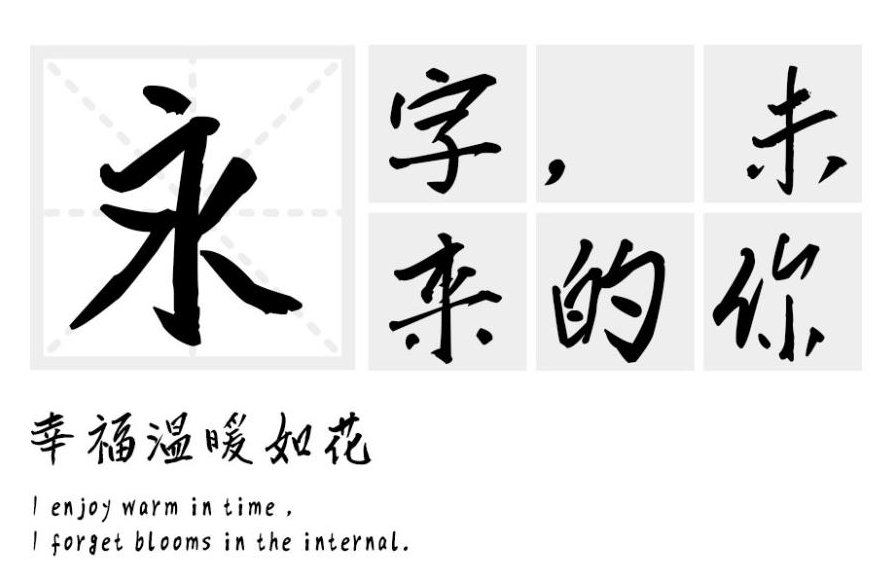
汉标儒雅楷书:这款字体设计遵循着中国传统技法,融合百家之长。浑然天成的字体风格,视觉效果典雅大方。字体结构严谨、比例合理,整体上给人一种舒展自如、赏心悦目的感受。适用于广告、屏幕显示、正文等方面。
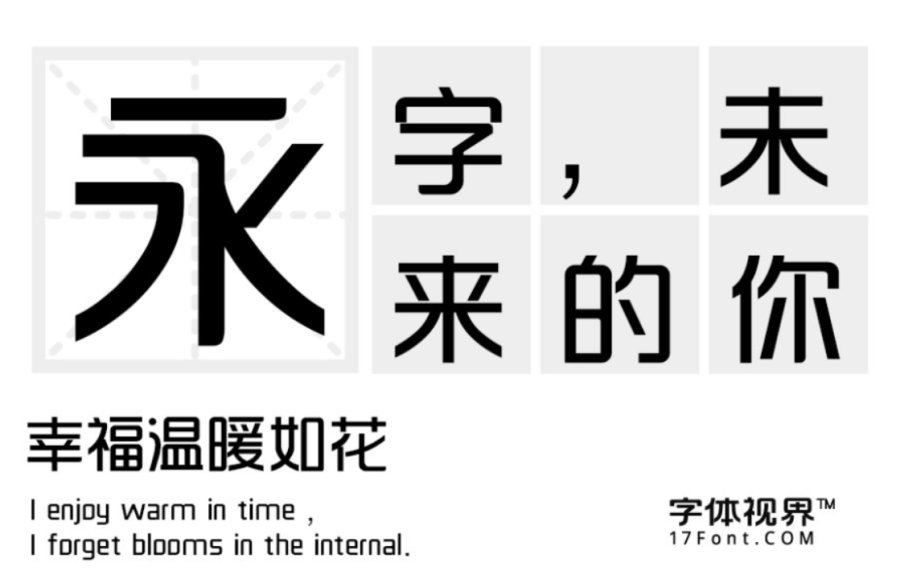
三极韵黑简体:这款字体的笔画轮廓由直线和转角弧线构成,横竖笔画交叉处和部分的收笔处的线条呈现圆弧形状,字形充满整个字面框,重心稳定。风格刚中带柔,粗中有细。适用于logo、广告、印刷、店面设计等方面。
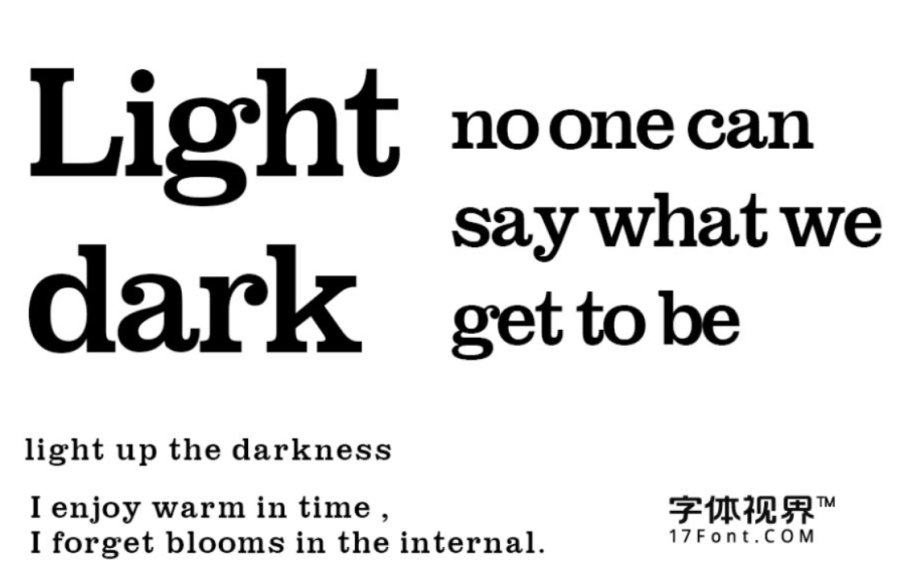
MItooh:这款字体是一款经典的英文字体。它的曲线和对角线设计精心具有很强的平衡性,字形宽度和间距比较大,稳重有力,字形清晰 。适用于广告、包装、印刷、屏幕显示等方面。